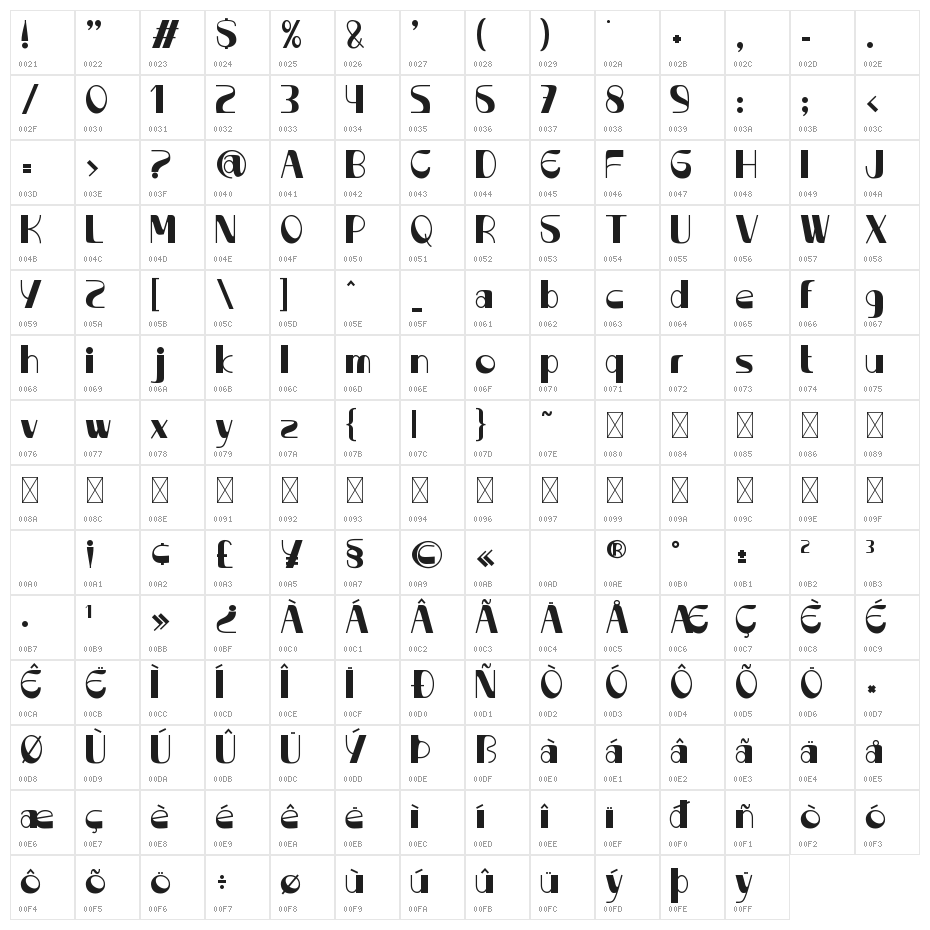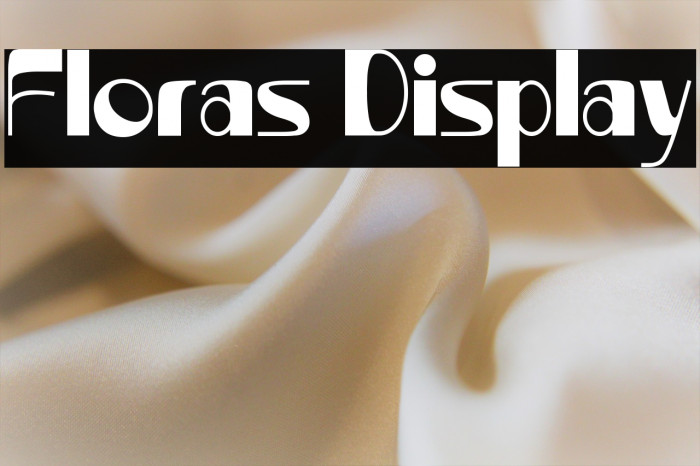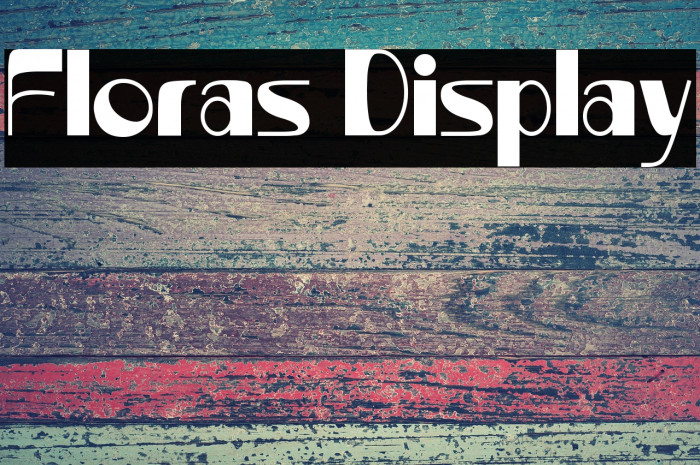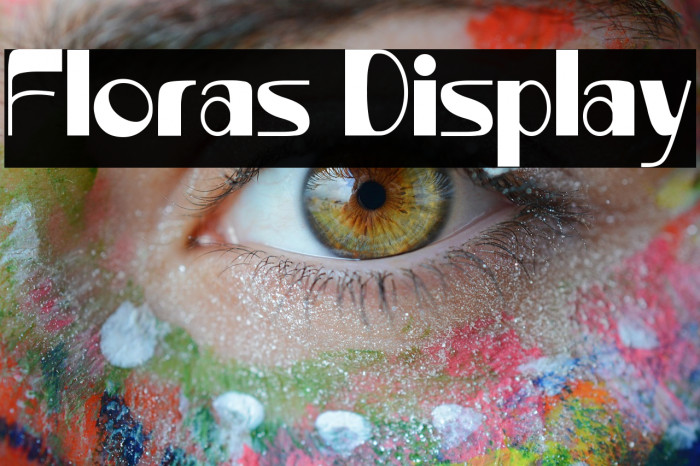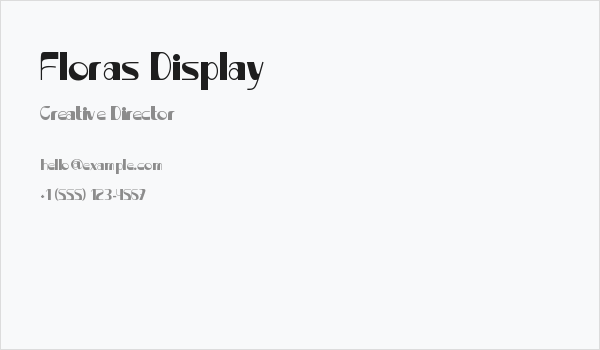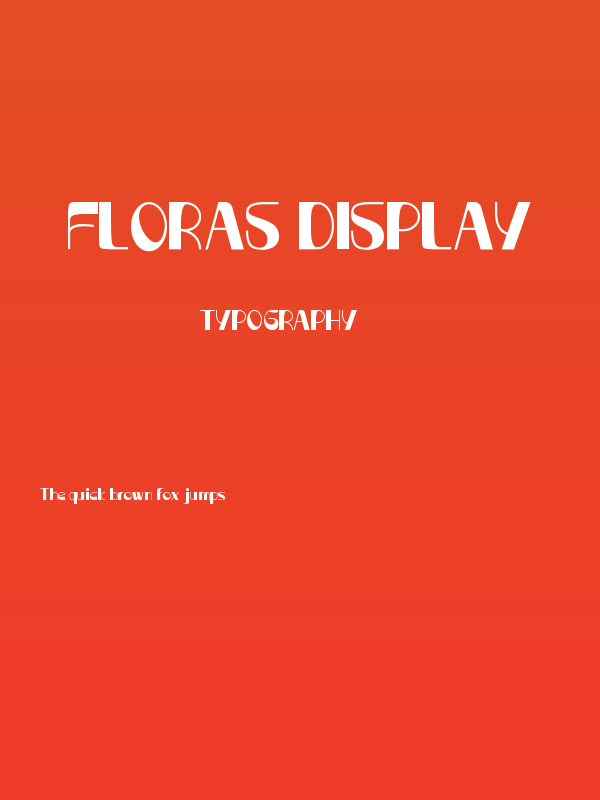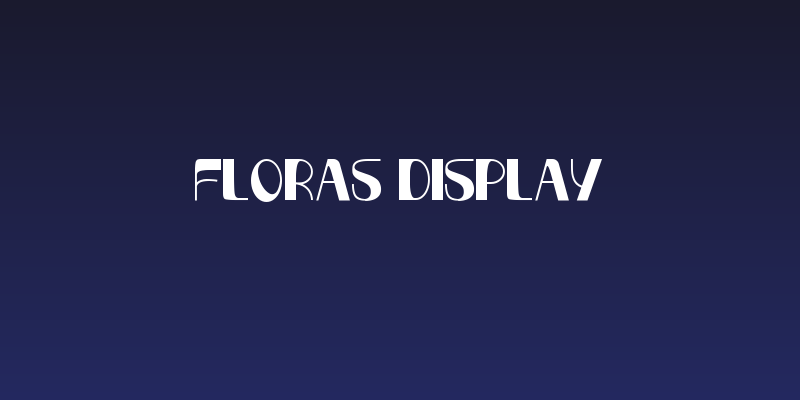
Floras Display Font
| Stile generale | Modern, Decorative |
| Progetti proposti | Ideal for branding, poster design, album covers, and any project requiring a bold, artistic touch. |